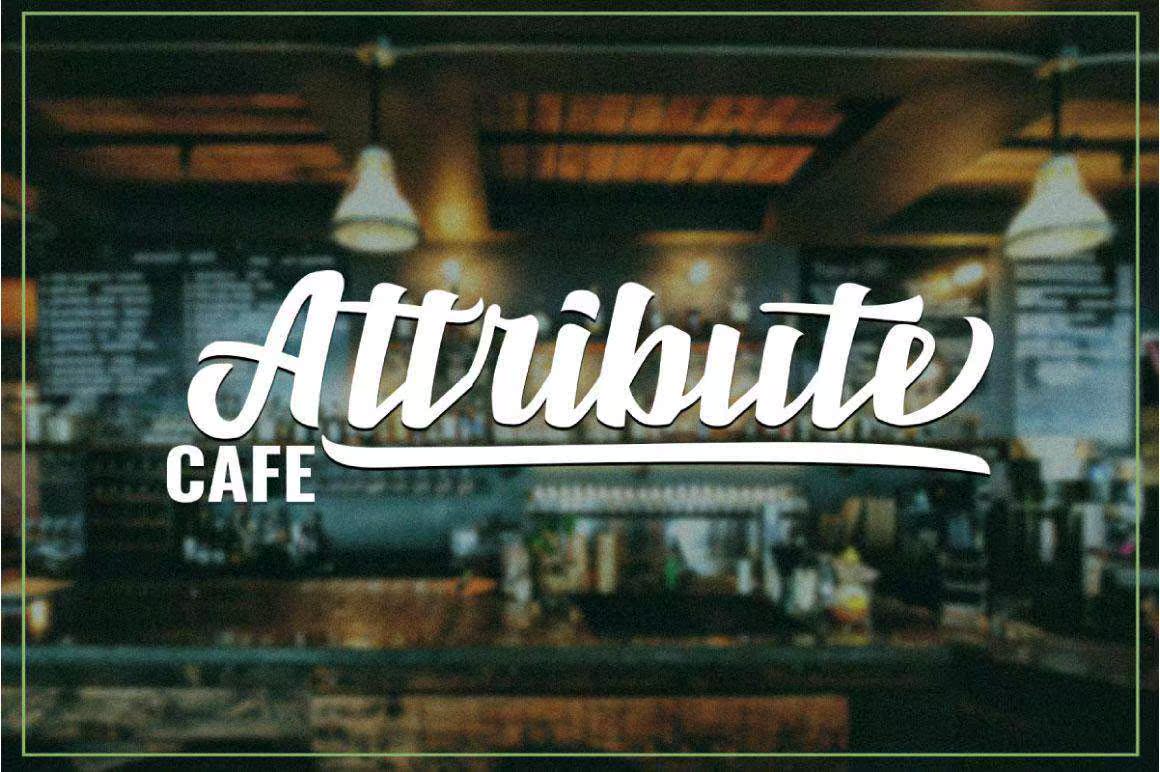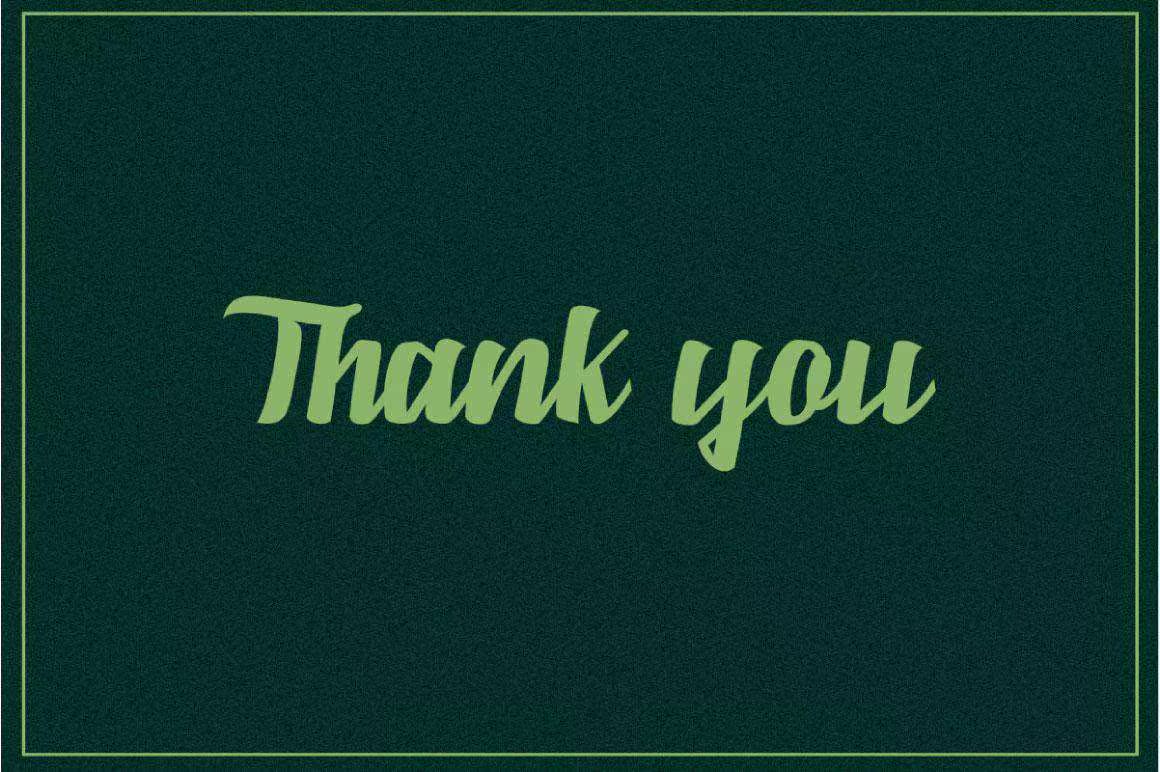
Marborn BoldScriptType Modern适合您的设计需求。此字体适用于徽标设计、t恤、品牌、社交媒体、缩略图、杯子、特百惠、手提包和各种其他设计用途。Marborn BoldScriptType Modern适合您的设计需求。此字体适用于徽标设计、t恤、品牌、社交媒体、,缩略图、马克杯、特百惠、手提包和各种其他设计用途。